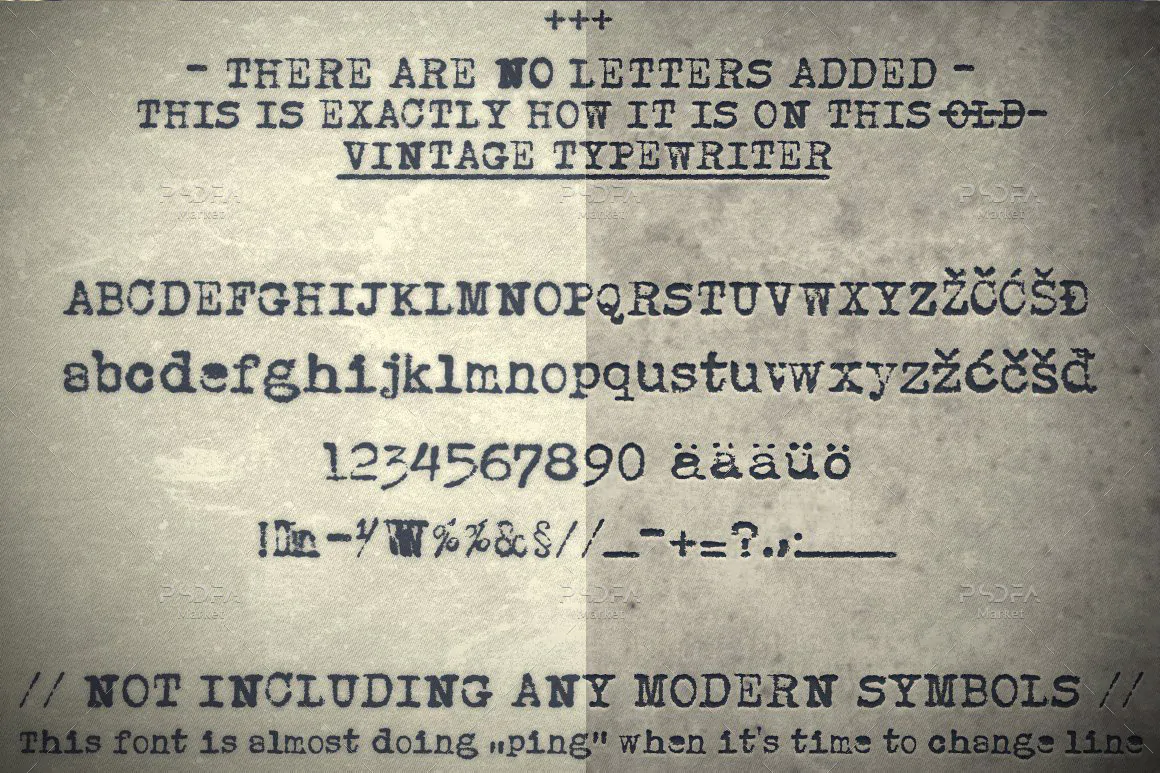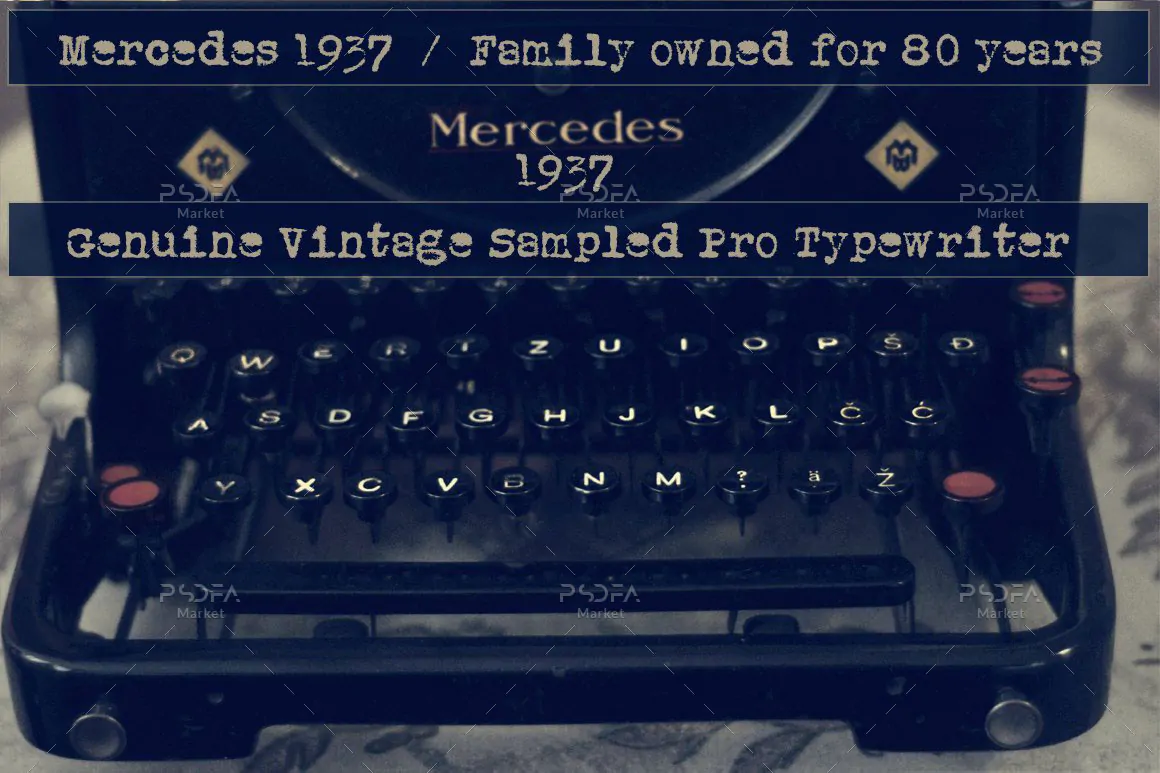
فونت ماشین تحریر قدیمی Mercedes1937
فونت ماشین تحریر قدیمی
فونت ماشین تحریر قدیمی Mercedes1937 یک سریف فونت انگلیسی به سبک ماشین چاپ قدیمی است که مناسب جهت استفاده در طرح و پروژههای گرافیکی مختلف میباشد. فونت Mercedes1937 با وزن معمولی طراحی شده است که میتوانید از آن در طراحی انواع پوستر، بروشور، تراکت، بنر، بسته بندی محصولات و … استفاده کنید.